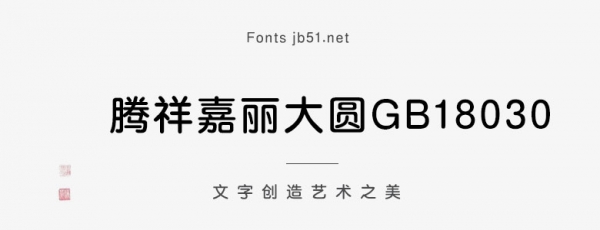
騰祥嘉麗大圓GB18030是一款不錯(cuò)的藝術(shù)字體,由騰祥字庫(kù)出品,該字體懷大但結(jié)構(gòu)并不松散,字面比傳統(tǒng)黑體飽滿但比舊式圓體小,適合應(yīng)用于藝術(shù)設(shè)計(jì)、平面宣傳設(shè)計(jì)、網(wǎng)頁(yè)設(shè)計(jì),書法字帖等領(lǐng)域,需要的朋友可以前來本站下載。
騰祥嘉麗圓體系列字庫(kù)是騰祥公司自主精心設(shè)計(jì)的圓體家族系列字庫(kù)。共有8個(gè)粗細(xì),各個(gè)粗細(xì)之間風(fēng)格一致,每款字庫(kù)數(shù)萬個(gè)字符風(fēng)格一致。字體風(fēng)格:其字懷大但結(jié)構(gòu)并不松散,字面比傳統(tǒng)黑體飽滿但比舊式圓體小,字形稍扁方但視覺上看似正方。每個(gè)字的轉(zhuǎn)角、圓頭、勾形都有極好的光潔度。筆型嚴(yán)謹(jǐn)、規(guī)范。每個(gè)字都經(jīng)過精心設(shè)計(jì),筆畫光潔柔美、粗細(xì)均勻、間架結(jié)構(gòu)端正、重心平穩(wěn)。